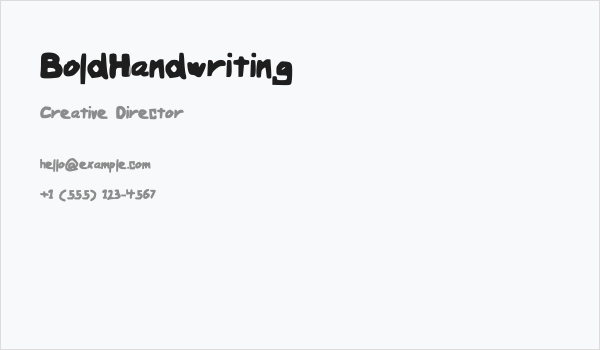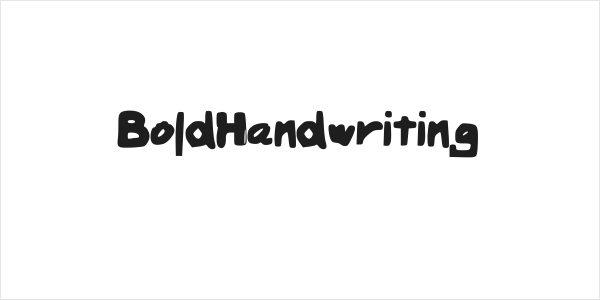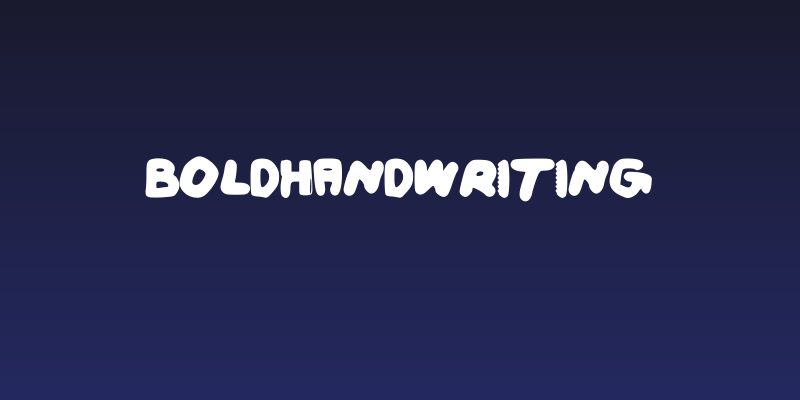
BoldHandwriting Font
| Gesamtstil | Playful, Expressive |
| Anwendungsfall | Headlines, Logos, Invitations |
| Vorgeschlagene Projekte | Ideal for invitations, greeting cards, playful branding, and personal projects. |